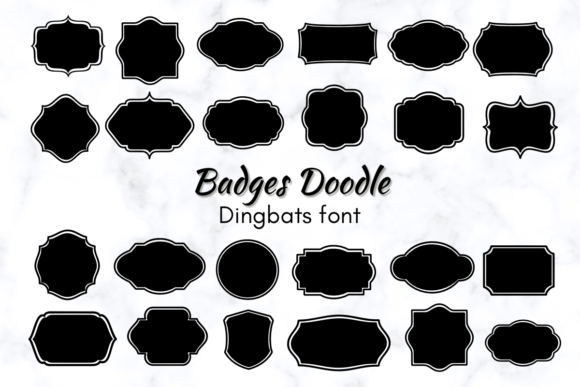
Badges Doodle
適切なデザイン要素を見つけるのは難しい場合がありますが、Badges Doodleは作品を即座に引き立てる優れたコレクションを提供します。
POD(オンデマンド印刷)製品、結婚式の招待状、またはソーシャルメディアのグラフィックを作成している場合でも、Badges Doodleは理想的です。